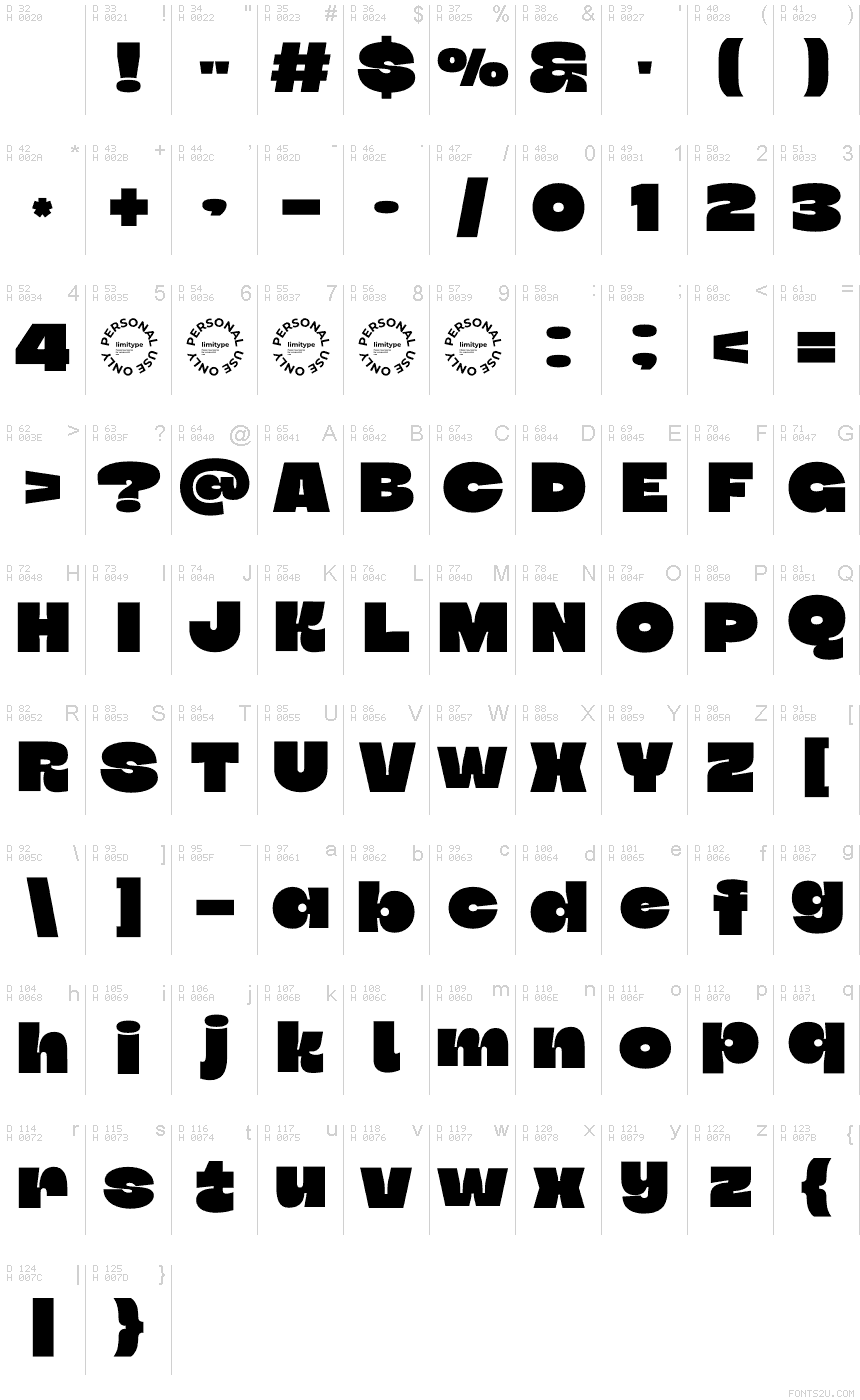
Skyvia Bold Police
Skyvia est une police de caractères display grasse dotée de formes de lettres massives et de détails d'inktrap distinctifs. Ses formes épaisses et compactes, combinées à des découpes ludiques, créent une personnalité visuelle amusante, énergique et expressive. Conçue pour marquer les esprits par un fort impact visuel, Skyvia est parfaite pour les affiches, les titres, les logos, l'image de marque, le packaging, les visuels pour réseaux sociaux, la publicité et les créations display accrocheuses.
Table des caractères de la police Skyvia Bold
Glyphes de la police Skyvia Bold — Latin de base, page 1